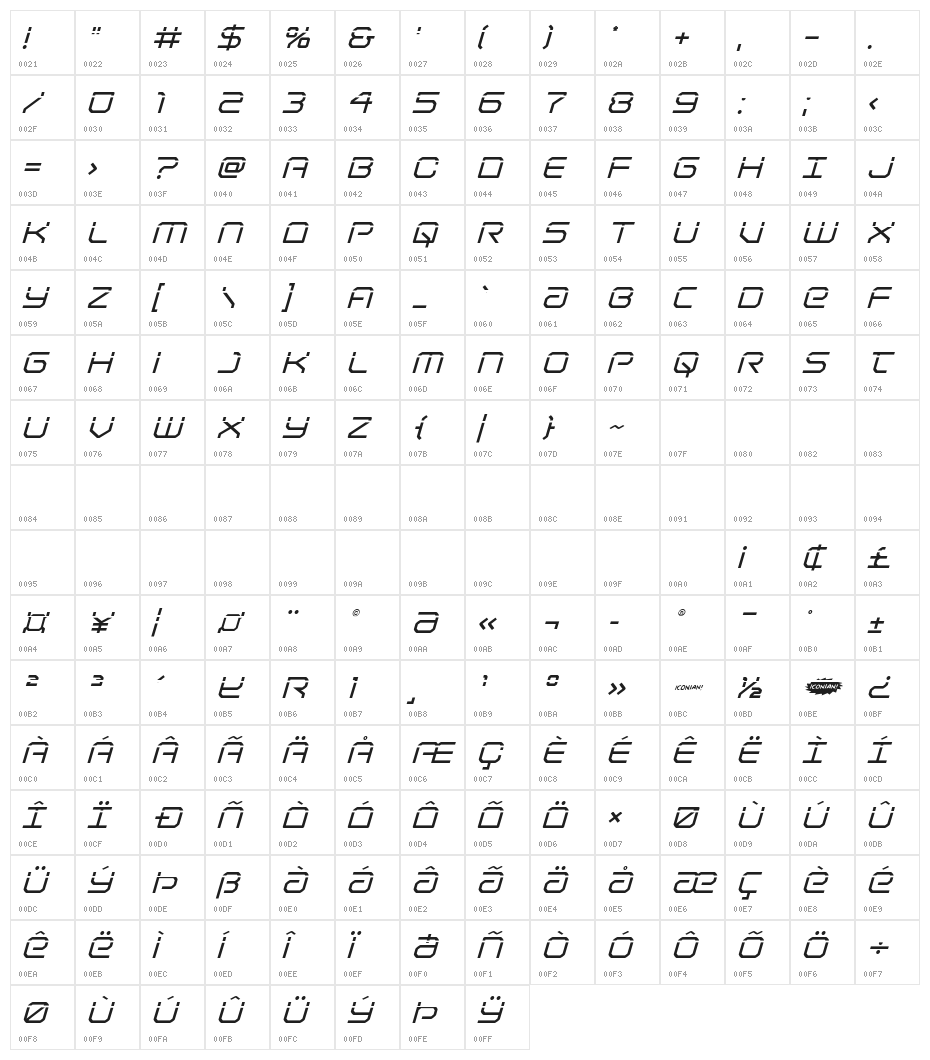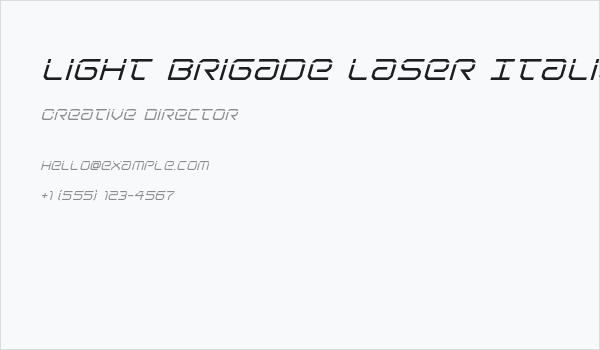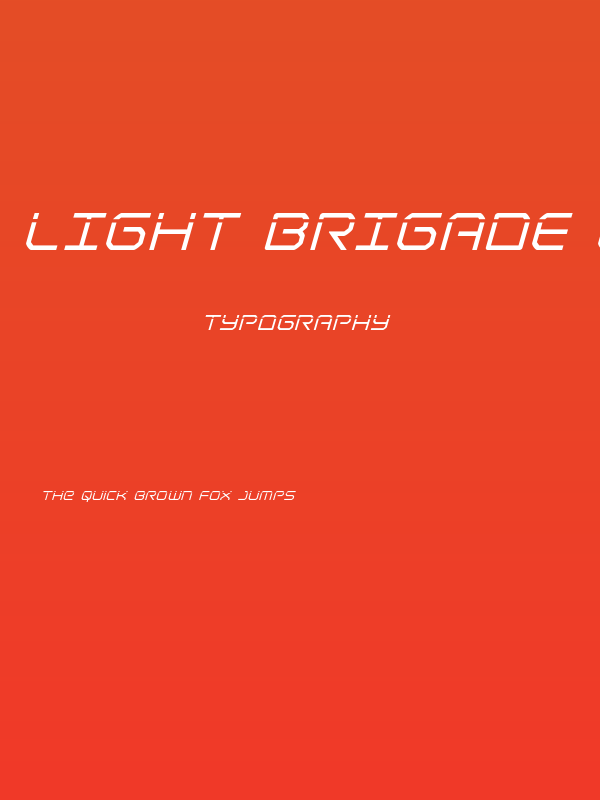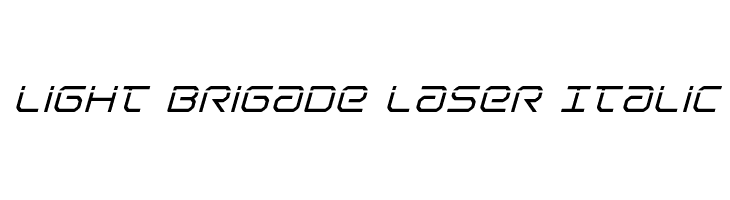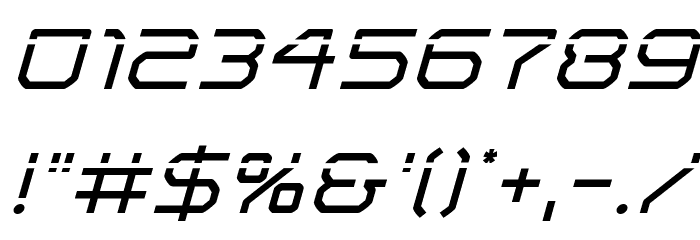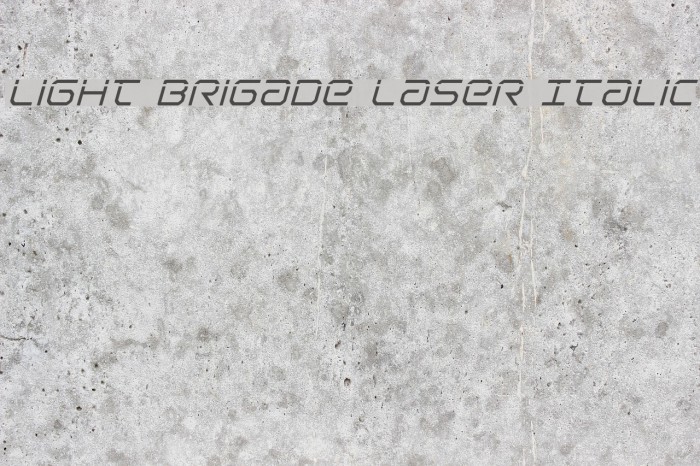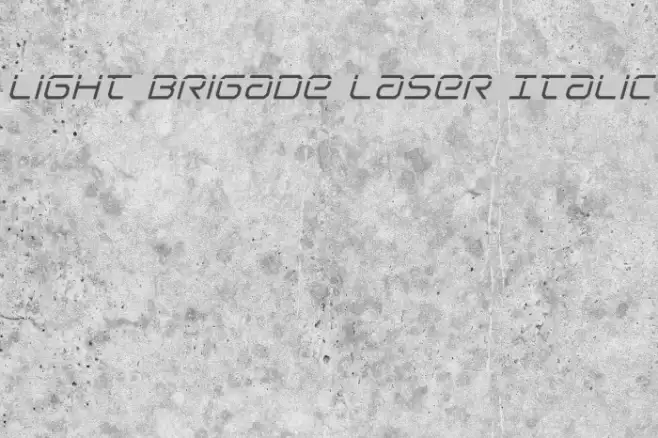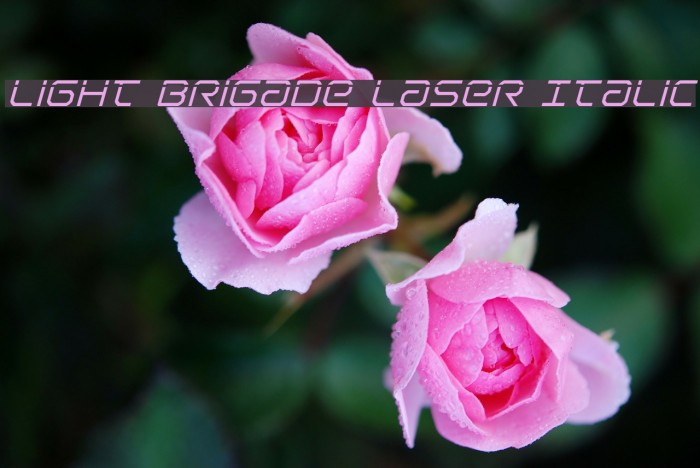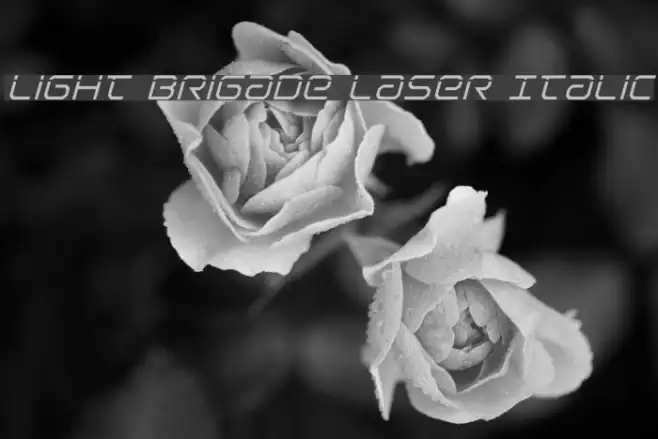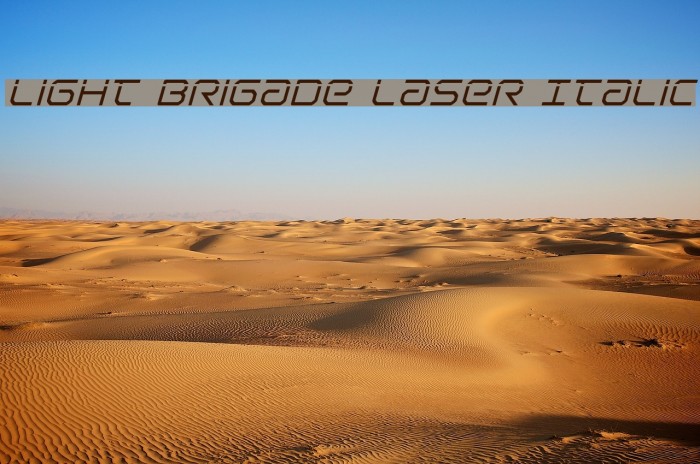
Light Brigade Laser Italic Font
| Proyectos propuestos | Ideal for technology branding, sci-fi themed designs, video game interfaces, and futuristic posters. |